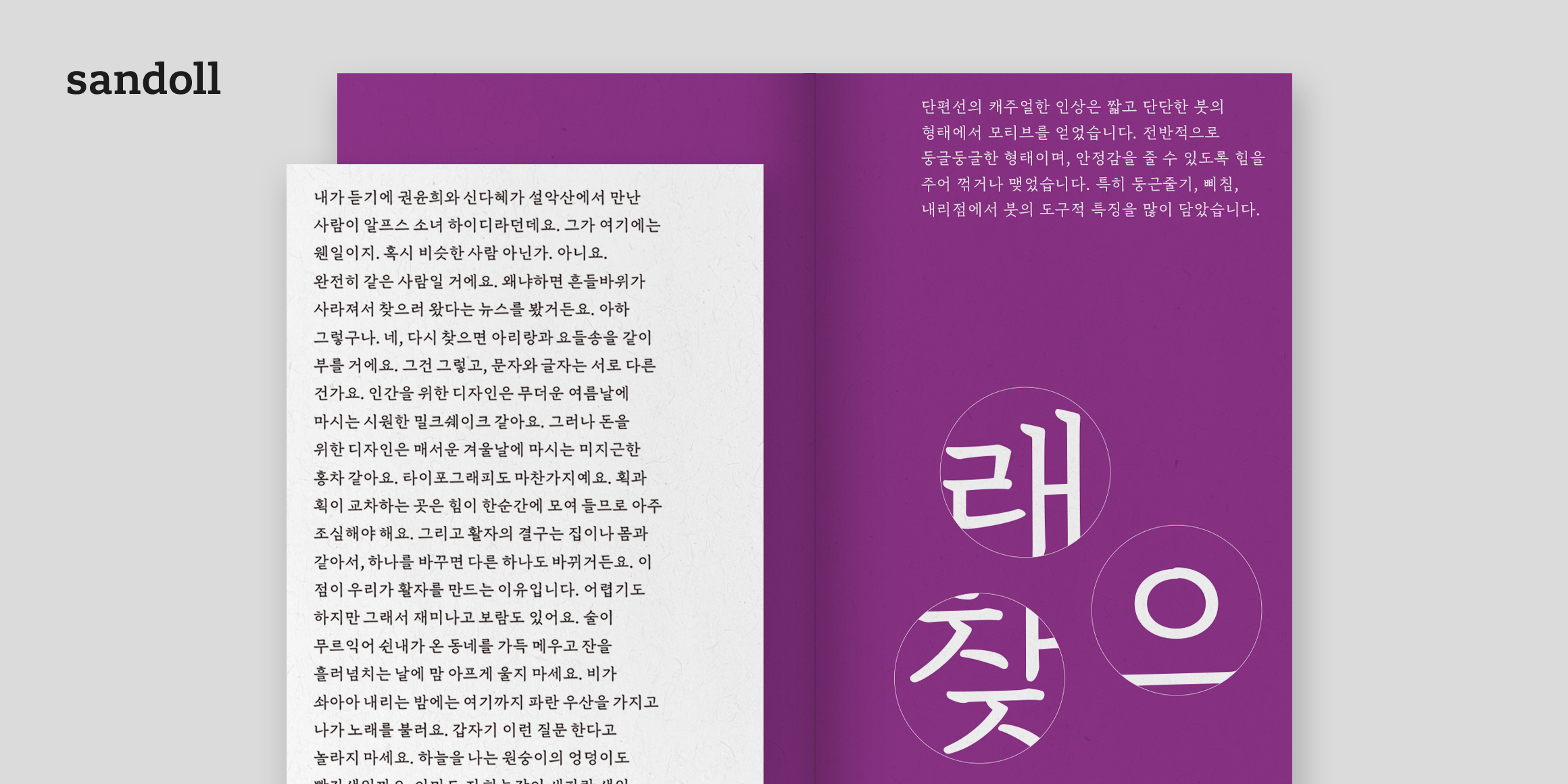
기존의 부리계열 폰트가 미려하고 곡선적인 인상을 갖고 있었다면 산돌 눈솔은 곧은 형태, 완만한 기울기, 넓은 받침 같은 구조들을 활용해 안정적이고 견고한 느낌을 준다.
제목과 본문에 모두 사용하기 편리하며, 조판했을 경우에도 부담스럽지 않고 편안하게 읽히는 장점을 지녔다.
산돌의 폰트 중 Adobe-KR-9 규격이 첫 번째로 적용되어 기존에 표현하지 못했던 뷁, 똠얌꿍 같은 표현들이 가능해졌다.
또한 기존의 Bold에 이어 Thin, Regular가 새롭게 추가되어 사용성이 확장되었다.